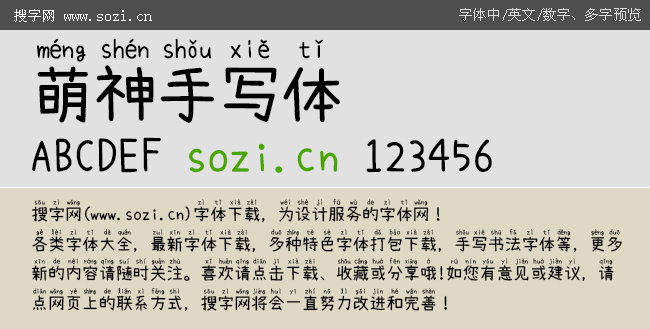
萌神手寫體
搜字網(wǎng)給大家提供一款萌神手寫體中文字體下載,萌神手寫體是用于學習中國漢字的一款字體,是使用小賴字體進行改造而成的一款免費商用字體。 這是一種用來幫助學生更快地學習和閱讀漢語的字體;旧鲜强梢燥@示日語、簡體字和繁體字的字體,是在簡體字和繁體字中加入拼音的字體的制作。適用于兒童繪本、書籍排版、包裝設(shè)計等應(yīng)用。